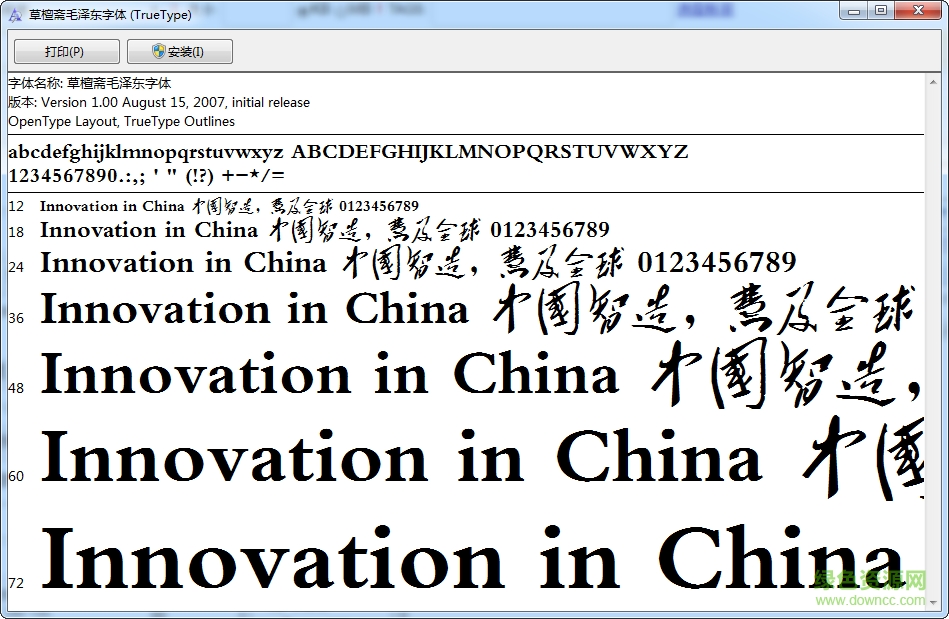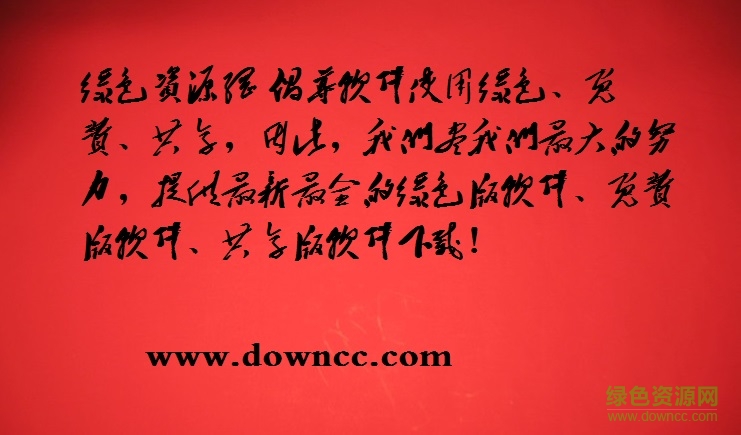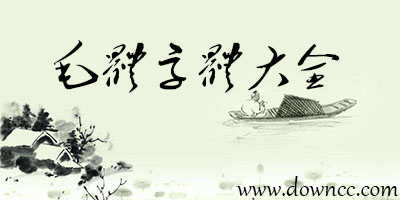
草檀齋毛澤東字體
草檀齋毛澤東字體。ttf,一代偉大領(lǐng)袖毛澤東主席的字體,他老人家的書(shū)法被后人制作為毛澤東字體,又稱(chēng)為草檀齋毛澤東字體。
毛澤東草書(shū)字體
毛澤東草書(shū)字體是一款偉大領(lǐng)袖毛主席的字體,毛主席草書(shū)風(fēng)格雄渾,力道蒼勁,在很多設(shè)計(jì)眼里都是電腦必備字體。
毛澤東毛筆字體
毛澤東二十世紀(jì)杰出書(shū)法家,他的書(shū)法在中國(guó)書(shū)法史上占據(jù)著重要地位,以其大氣磅礴,氣貫長(zhǎng)虹的風(fēng)格,深受廣大書(shū)法愛(ài)好者的喜愛(ài)。